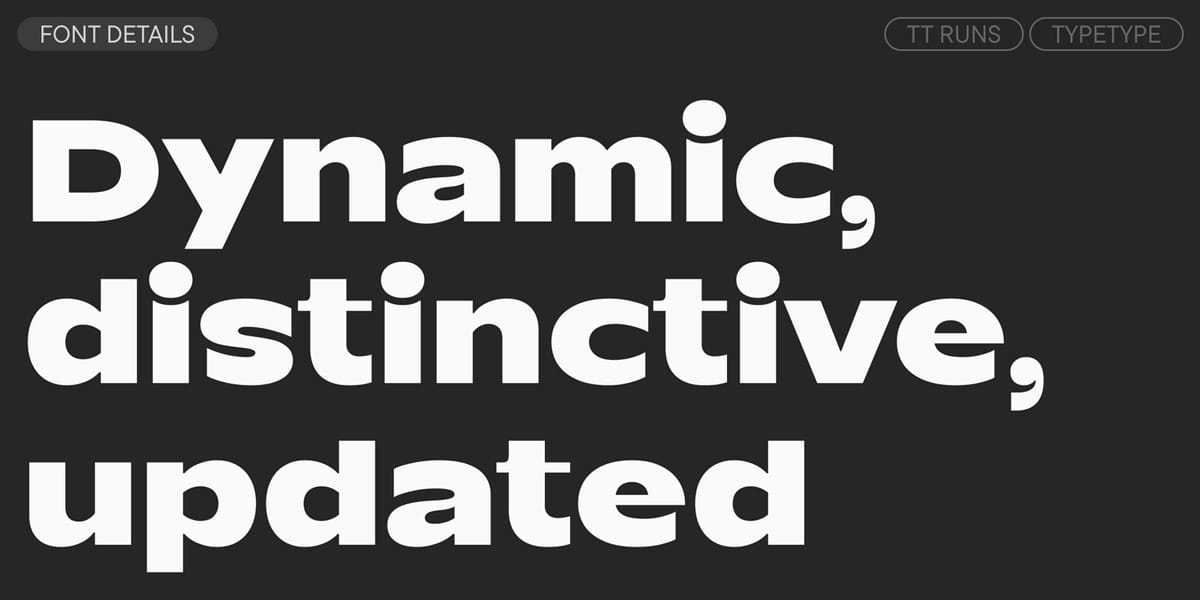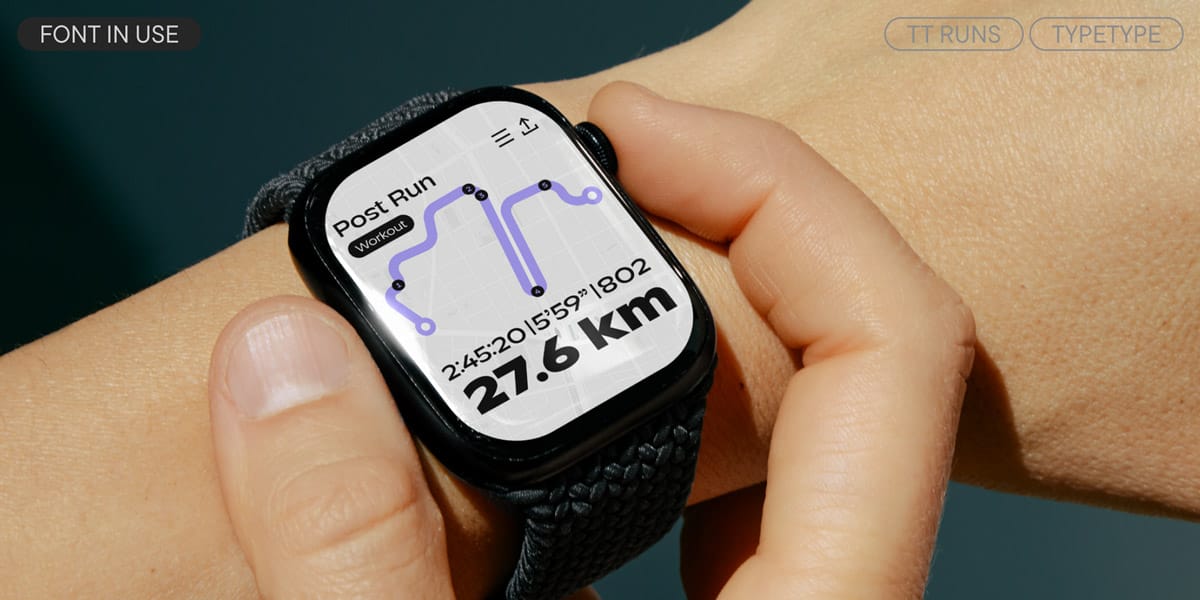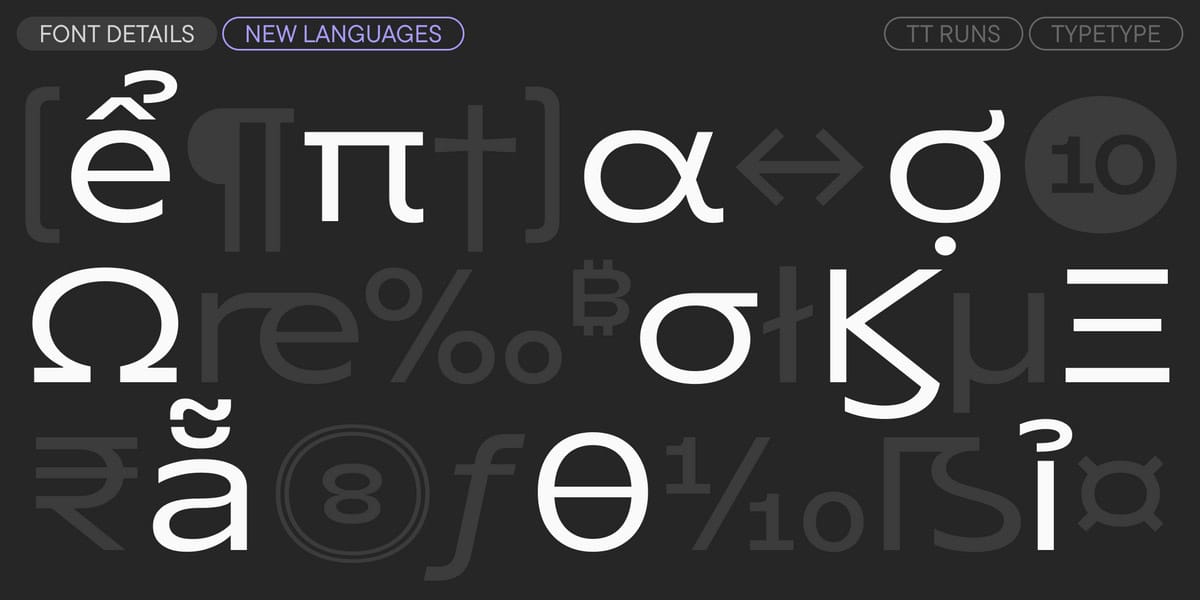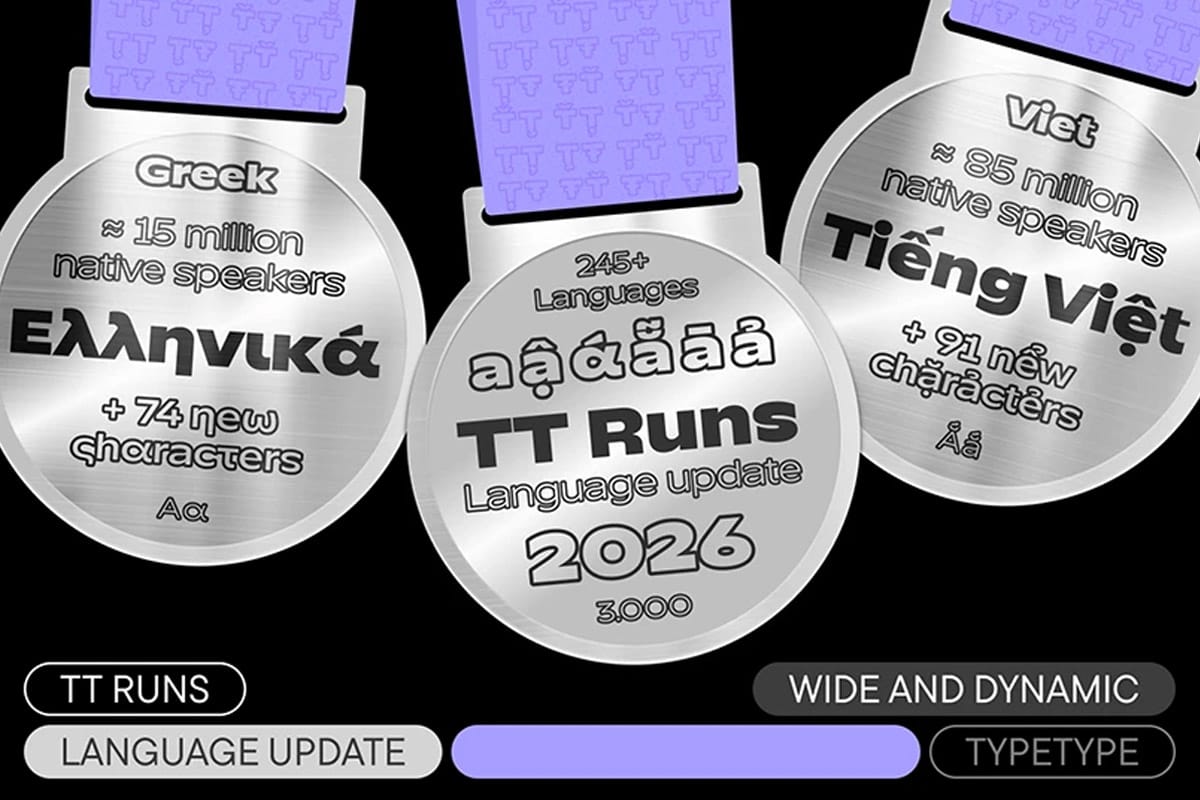
TT Runs là bộ font sans-serif dáng rộng (wide), hiện đại do TypeType phát triển và tối ưu cho mảng thể thao, lifestyle năng động, branding và poster display. Phiên bản mới nhất hiện tại là TT Runs 3.000, mở rộng bộ ký tự lên 1.160 glyph/style, bổ sung tiếng Việt cùng nhiều ký hiệu tiền tệ mới, đồng thời tinh chỉnh kerning/hinting để trải nghiệm hiển thị tốt hơn.
Lịch sử và thiết kế của font TT Runs
TT Runs ra mắt lần đầu năm 2020 và được xây dựng với định hướng rõ ràng cho ngành thể thao. Trước khi thiết kế, đội ngũ TypeType đã nghiên cứu nhận diện thị giác ở nhiều địa điểm thuộc Olympic Games, phân tích các brand thể thao đương thời và theo dõi sự tiến hóa của typography “sports” qua nhiều thời kỳ, khu vực. Nhờ đó, TT Runs mang một “DNA” rất đặc trưng: tỷ lệ chữ rộng, cảm giác chuyển động mạnh, và tinh thần tự tin – cực hợp cho headline, logo wordmark và key visual.
Thiết kế nổi bật của TT Runs bao gồm:
- Inverse (reverse) contrast: tương phản ngược dễ thấy ở các weight đậm (một số nét ngang “nặng” hơn tương quan so với nét dọc), tạo cảm giác lạ mắt và giàu năng lượng. Ở chữ thường, cảm giác này được làm dịu để giữ độ đọc.
- Các chi tiết letterform nhận diện cao: chân thẳng ở “R”, dáng “M” sắc, “G” khác thường, bộ dấu (diacritics) được “nén” gọn ở các master đậm… giúp chữ nhìn rất “sports” khi lên kích thước lớn.
- Ligatures chọn lọc: một số liên kết chữ cái giúp headline mượt hơn và tạo nhịp thị giác tốt hơn khi dàn trang.
Cập nhật mới nhất trong phiên bản 3.000
TT Runs 3.000 tập trung vào việc mở rộng khả năng sử dụng thực tế (đa ngôn ngữ, đa ngữ cảnh) thay vì thay đổi “DNA” thị giác. Các điểm update đáng chú ý:
- Tăng số lượng glyphs: từ 917 lên 1.160 glyphs/style. Bổ sung minuscule currency symbols và thêm đầy đủ các đồng tiền Som, Sum, Dong cho mọi dạng chữ hoa/thường cần thiết.
- Mở rộng hỗ trợ ngôn ngữ: nâng lên 245+ ngôn ngữ, trong đó có thêm Urum, Greek và Vietnamese – đặc biệt hữu ích nếu bạn thiết kế cho thị trường Việt Nam.
- OpenType features: điều chỉnh về mức 30 tính năng (hệ ss/ligatures/số…).
- Cải thiện kerning & hinting: được cập nhật một phần để hiển thị ổn định hơn trên nhiều môi trường.
- Variable Font: tiếp tục hỗ trợ font biến thiên với 2 trục weight và slant (độ nghiêng), cho phép tinh chỉnh “độ nặng” và “độ chuyển động” chỉ bằng một thanh trượt.
Nhờ các cập nhật này, TT Runs 3.000 phù hợp hơn cho các dự án đa ngôn ngữ, thiết kế có nhiều con số/ký hiệu, và đặc biệt là workflow branding cần font display “đậm chất sports”.
Tính năng nổi bật của bộ font TT Runs
- 19 styles: gồm 9 upright, 9 italic và 1 variable font. Dải trọng lượng đa dạng giúp bạn đi từ hệ chữ “clean” đến headline cực lực.
- Bộ ký tự mạnh: 1.160 glyphs/style, hỗ trợ tiếng Việt và nhiều ngôn ngữ; đồng thời có thêm nhiều ký hiệu số, dấu câu, ký hiệu toán học, mũi tên và hệ ký hiệu tiền tệ (bao gồm cả đồng ₫).
- OpenType features (30): có các nhóm tuỳ chọn hữu ích như stylistic sets (ví dụ ss01), các kiểu số khoanh tròn/biến thể số, ligatures… và một số tuỳ chọn localization.
- Ứng dụng lý tưởng: sports branding, poster giải chạy/fitness, esports key visual, áo đấu/merch, packaging “athletic”, và các chiến dịch cần headline mạnh.